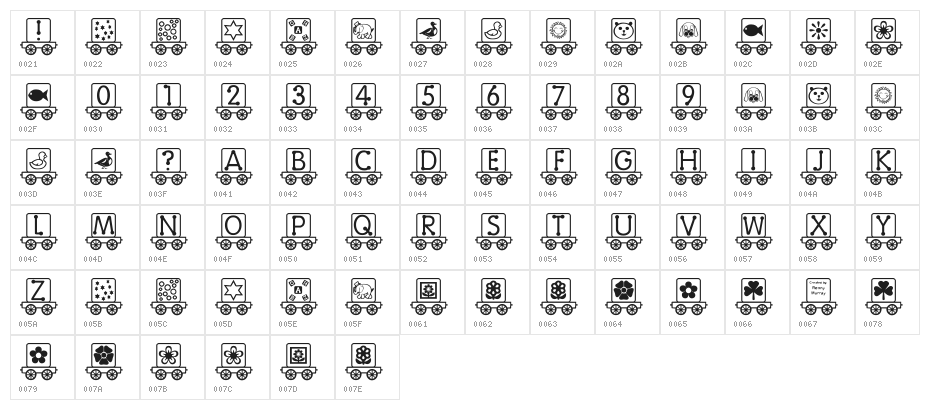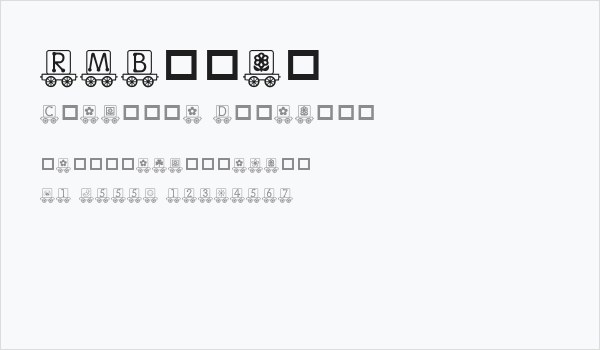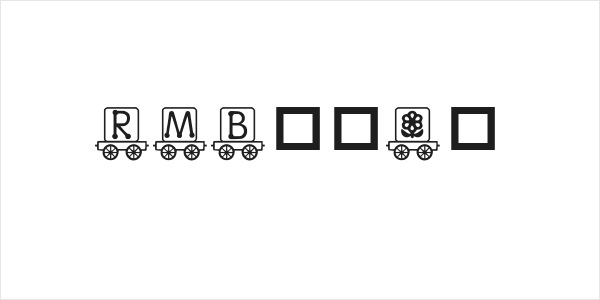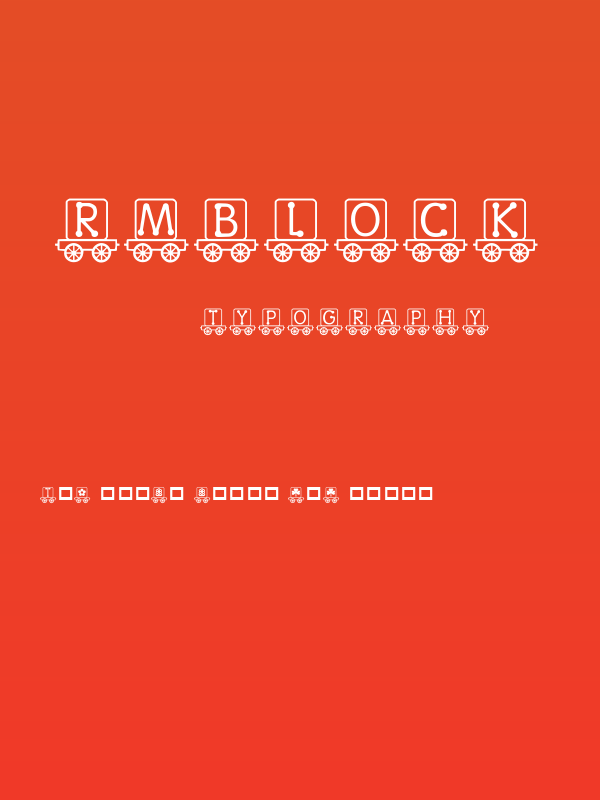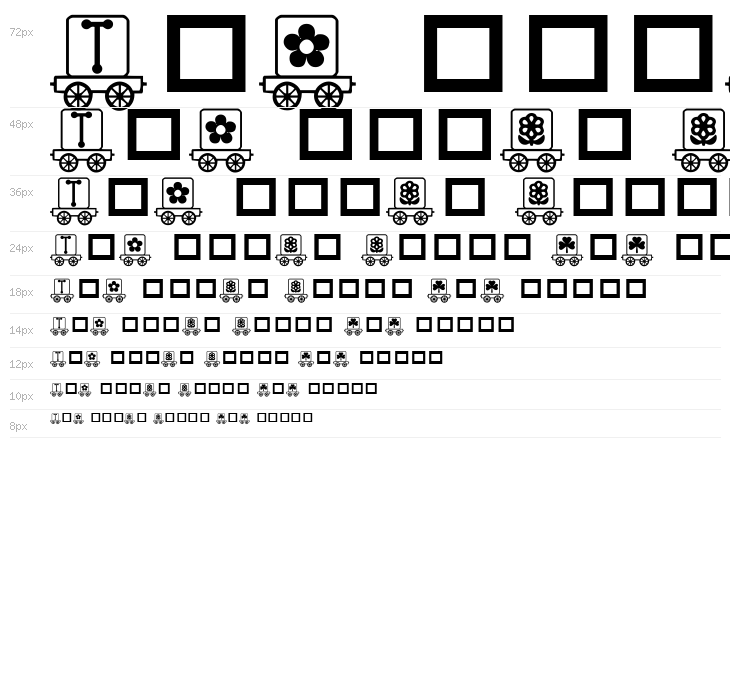
RMBlock Font
| Stile generale | Playful, Whimsical |
| Caso d'uso | Headlines, Logos, Children's materials |
| Progetti proposti | Ideal for children's books, educational materials, toy packaging, and playful branding projects. |